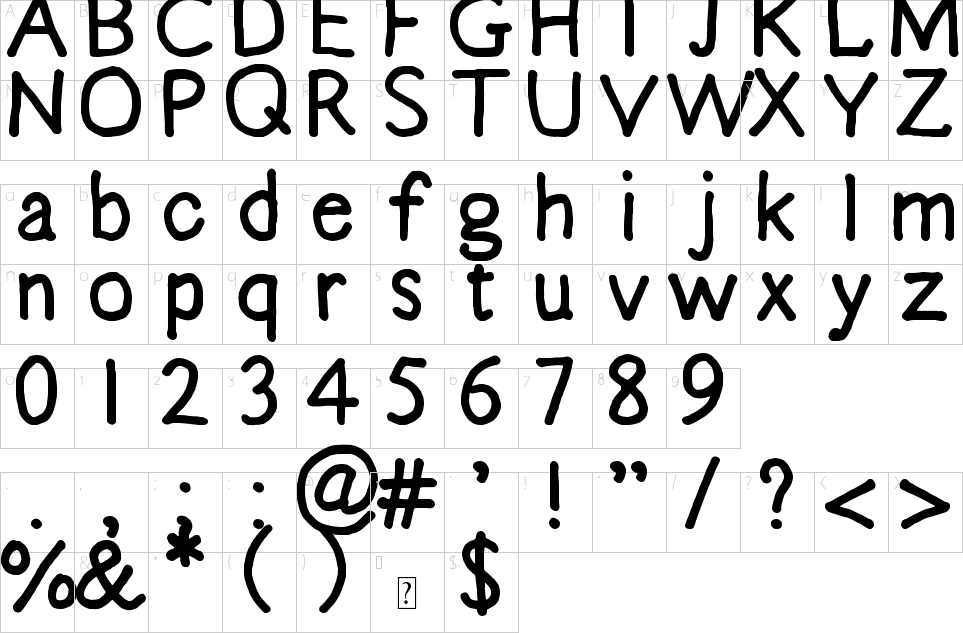
A fonte ‘Emma Sophia’ é uma opção gratuita e elegante para designers que buscam adicionar um toque sofisticado a seus projetos digitais. Desenvolvida pelo designer anônimo de 1001 Free Fonts, Emma Sophia está disponível tanto para Windows quanto para Mac, tornando-a acessível para todo o mundo. Sua elegância e legibilidade fazem dela uma excelente escolha para qualquer projeto gráfico, seja ele para aplicativos móveis, sites ou design tipográfico tradicional. Com um total de 7,604 downloads únicos, Emma Sophia já foi adotada por muitos designers ao redor do mundo. Se você está procurando uma fonte que traga um ar refinado e moderno aos seus trabalhos, ‘Emma Sophia’ é uma excelente escolha para dar ao seu design um toque de sofisticação sem comprometer a legibilidade.